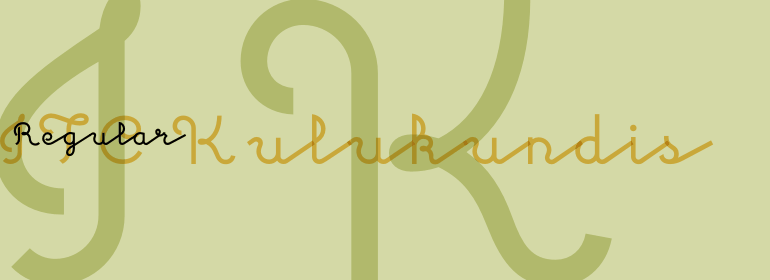
ITC Kulukundis™
ITC Kulukundis™,这款字体结构工整、笔画清晰,兼顾美观与易读性,适用于标题、正文、海报、包装、LOGO 等多种场景。字形优雅稳定,风格百搭耐看,适配日常排版与创意设计,让文字呈现更舒适、更具质感。ITC Kulukundis™一笔一画,皆是细节,以均衡的比例、流畅的线条打造舒适视觉体验,字形端正大气,风格简约现代。无论是商业设计、品牌宣传还是日常排版,都能轻松驾驭,让文字更有格调与力量。ITC Kulukundis™字体下载。
字体品牌: ITC(Monotype) 设计师:Pelavin,Daniel 字体分类:手写风格字体 字体属性:外文 字符集:Unicode 发布时间: 2018